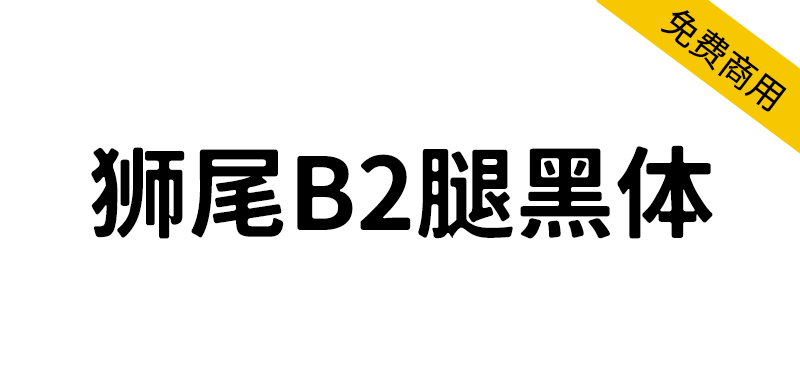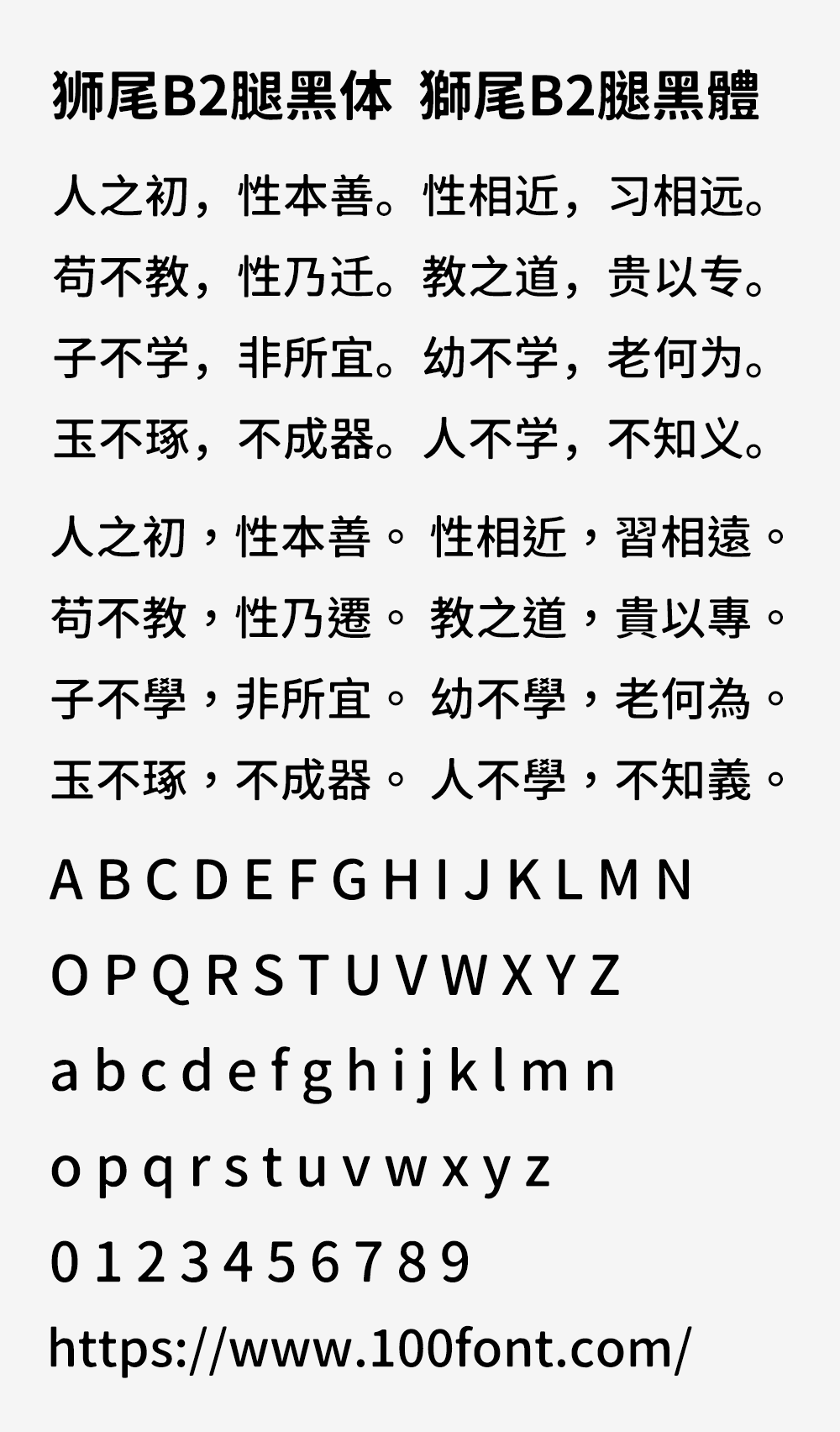
狮尾B2腿黑体基于思源黑体的转角的三角形转成半圆形改造,腿黑指没被拔脚的黑体,仿佛墨晕或是稍微过曝的效果。和思源黑体一样,有7种字重,支持简体中文、繁体中文、韩文与日文,可以免费商用,欢迎大家自由应用、自由优化、自由改作!
狮尾B2腿黑体和「狮尾B2黑体」差别在有没有拔脚,「拔脚」就是会有较少的笔画,例如移除「口」字的左右下角会多出的短线条。有拔脚的字会较圆,但是会造成有些字因直接去掉腿后左右不平衡、左右不对衬的「悬空」问题。改使用「腿」系列字体就不会有这个问题。